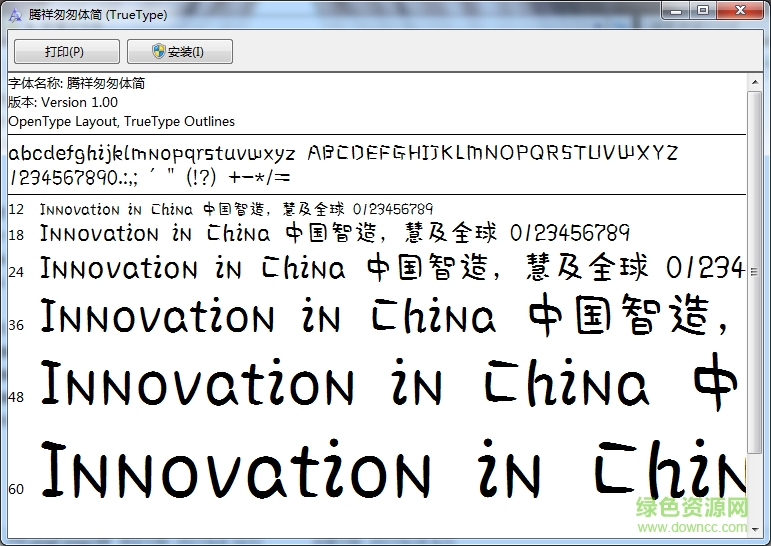
騰祥匆匆體是一款全新的藝術(shù)字體,字跡活潑造型別致,給人極佳的視覺呈現(xiàn),讓你的文字內(nèi)容更具個(gè)性色彩,喜歡的朋友來綠色資源網(wǎng)即可搶先體驗(yàn)哦!
騰祥匆匆體,中文簡體,字庫豐富,是騰祥字體系列的其中一種,可以用于印刷字體,海報(bào)字體等等。整體設(shè)計(jì)較為柔和,這廣告中有著個(gè)性的外觀和時(shí)尚的獨(dú)特韻味。